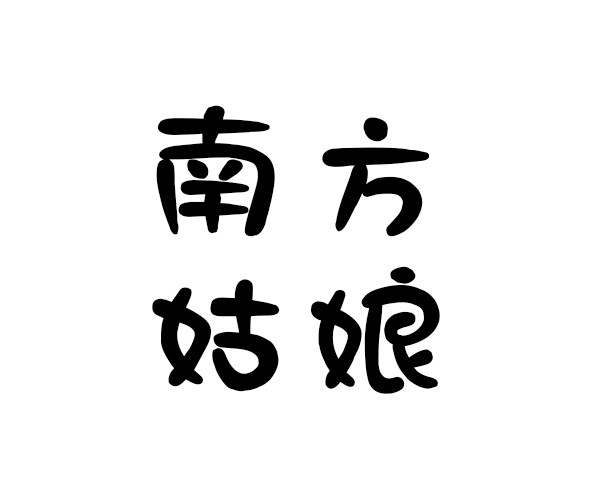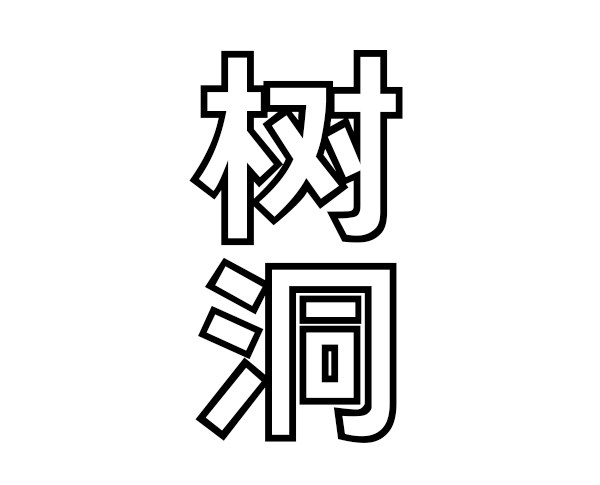
用手写体记录生活
字体是有性格的,不同的字体代表着不同的情感,在生活中,当我们不管是遇到开心的还是伤心的事情,我相信,大多数人还是会愿意用纸笔记录下来,手写体便成了人们情感的载体。字体视界愿和你一起见证每个时刻。
当我们想心爱的姑娘时,会说:我多么想和你见一面,看看你最近改变
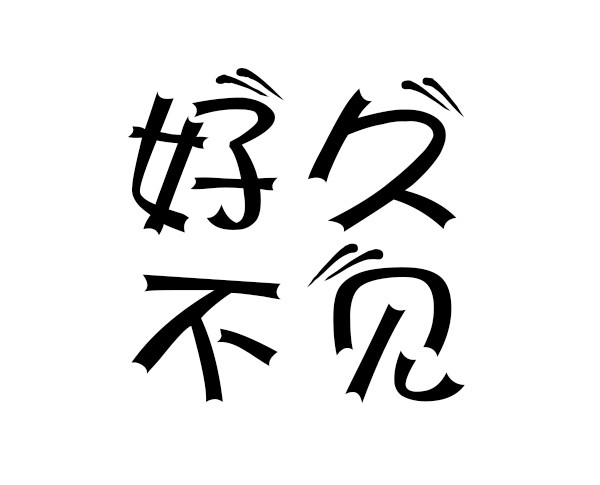
遇见体
百变马丁
当我们感叹时间流逝,父母老去时,想说:时光时光慢些吧,不想让你再变老啦,我愿用我一切,换你岁月长留
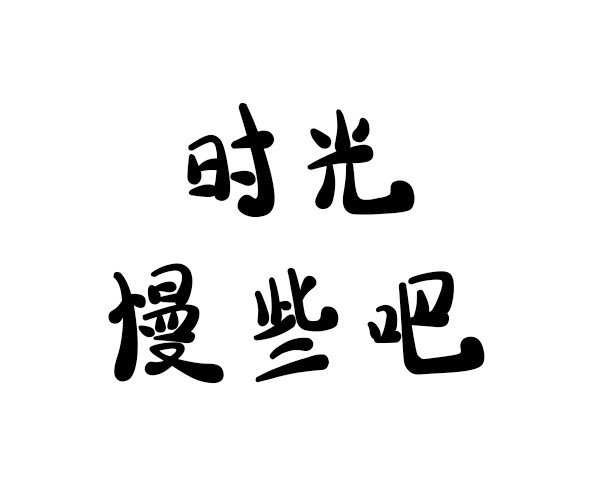
点点墨体
当我们感慨生活过于疲惫时,却想找个地方倾诉:我愿成为你的倾听者
义启白加黑